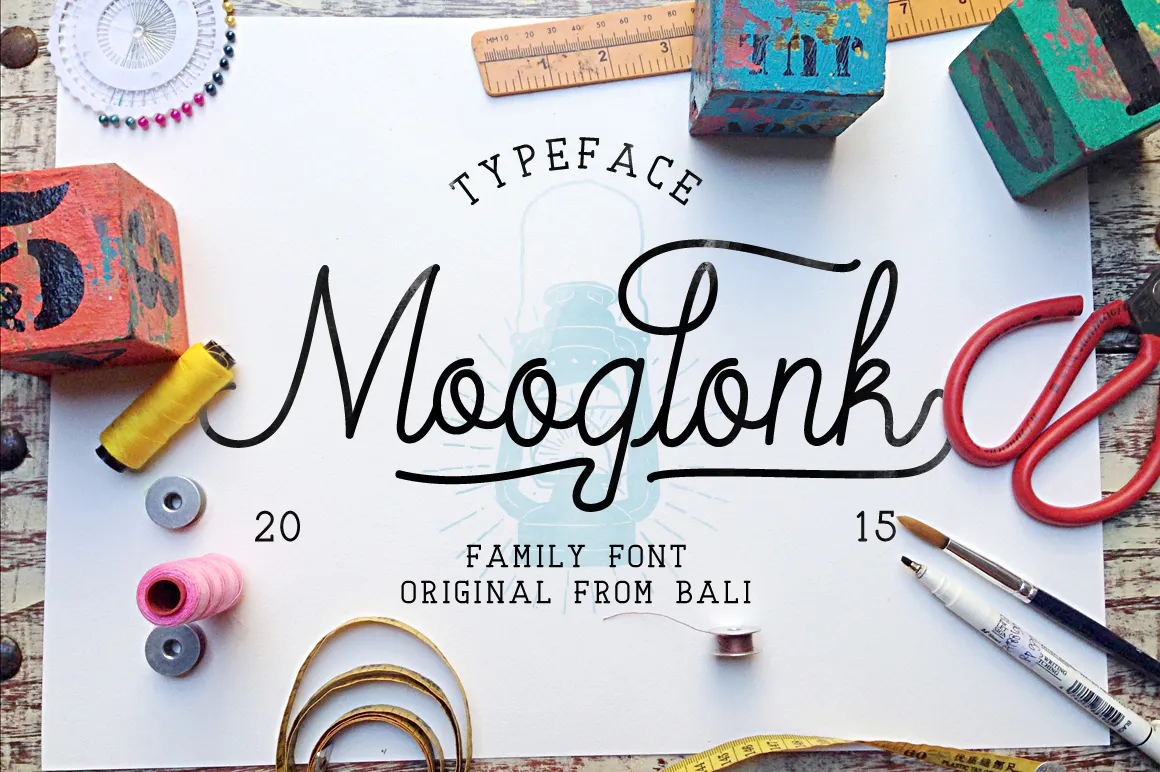
Mooglonk Font – Download Grátis
A Mooglonk Font é uma elegante fonte à mão que traz características autênticas do estilo humanoide para seus projetos digitais. Ideal tanto para uso pessoal quanto comercial, esta fonte livre pode ser usada de forma ilimitada e sem restrições. Uma pequena contribuição também é muito apreciada, e você pode encontrar mais opções excelentes em minha loja criativa no link fornecido. Para obter a versão completa da Mooglonk Font, visite o link que aparece na descrição original. Além disso, fique atento aos lançamentos de novas peças artísticas em meu portfólio através dos updates do Instagram, siga-me lá para não perder nenhum detalhe importante. Acreditamos que a Mooglonk Font é perfeita para estilos modernos e criativos. Ela irá trazer um toque autêntico ao seu design sem ser excessivamente complicado. Além disso, o designer Hamilton é uma referência clara neste tipo de fonte única e divertida. Não deixe de visitar minha loja online para encontrar mais opções incríveis de fonts e gratuitos úteis. Aqui está o link: https://creativemarket.com/alitdesign/273732-Mooglonk-Font-Badges-Brush Se você estiver interessado em me ver no Instagram, aqui está o link da minha conta: https://www.instagram.com/alitsuarnegara/ Essa fonte é um excelente complemento para qualquer projeto e eu acredito que vai ser uma opção ótima para aqueles buscando algo único e charmoso.